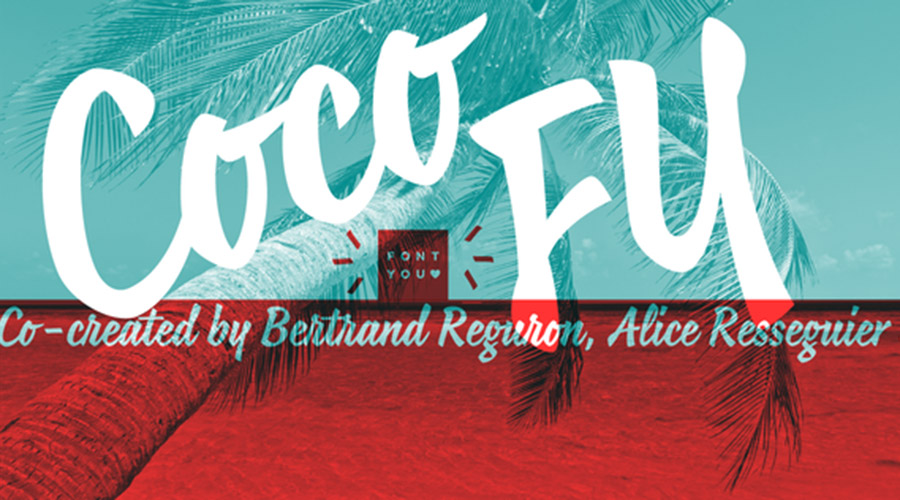
Coco FY là font chữ photoshop việt hóa theo phong cách Vintage cổ điển được sử dụng phổ biến trong thiết kế website, bảng hiệu, biển quảng cáo và các bảng hiệu tại các nhà hàng theo đuổi phong cách này. Ngoài ra, Coco FY là một lựa chọn tuyệt vời để thiết kế tem nhãn và bao bì theo ý tưởng.